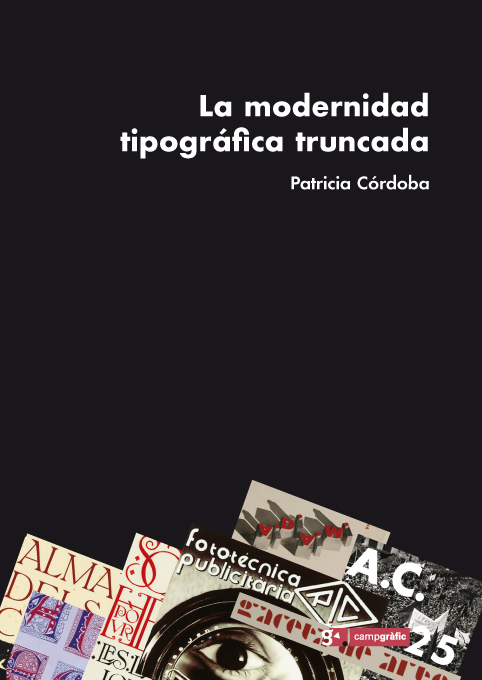
La modernidad tipográfica en España excede los movimientos que la Historia en mayúsculas ha encasillado en el período que abarca las seis décadas que van desde 1880 hasta 1939. El modernismo y el novecentismo catalanes fueron los dos movimientos más reconocidos. Hubo otros. Aislados, como el caso de Canarias. Más engrazados, como Valencia y Madrid. Pero siempre exponentes de un deseo compartido de modernizar una España anclada en el incensiario y la sotana, pero al mismo tiempo pigmentada de modernidades individuales.
El lector encontrará en estas páginas posicionamientos ideológicos, manifiestos y rupturismos que fueron aprovechados con fines políticos, a los que muchos incautos solo se han acercado desde la óptica de blancos y negros sin apenas matices.
Escrito con rigor, la autora, sin falsos espejismos ni rehechuras, recorre revistas, libros, carteles, técnicas y manifiestos de una época con evidentes muestras de modernidad en el diseño gráfico… y que primero la dictadura de Primo de Rivera retrasó, y después la de Franco definitivamente truncó.